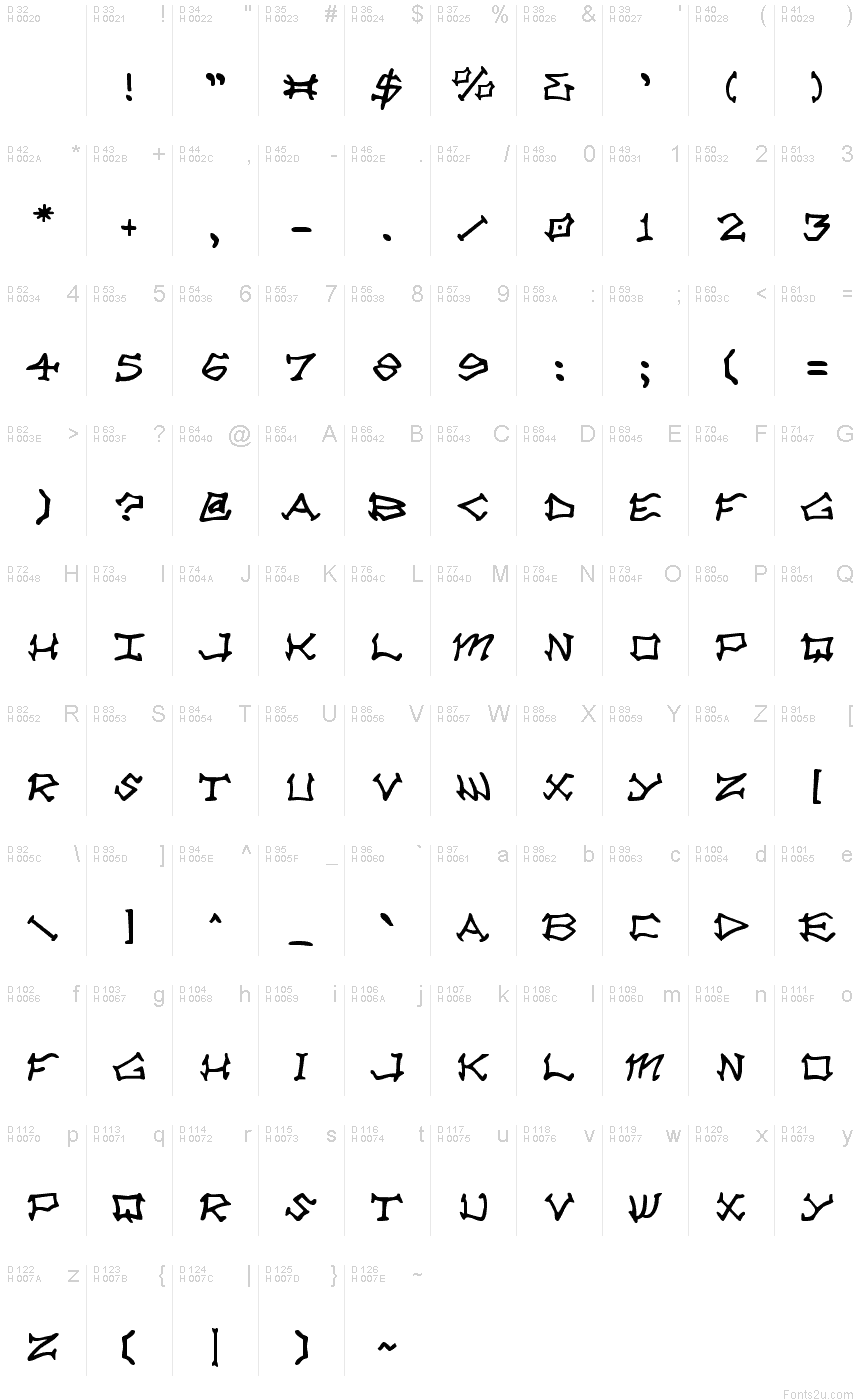
معاينة خط Rad Zad
خط Rad Zad من Iconian Fonts هو خط مجاني مستوحى من كتابات الجرافيتي اليدوية، يتكون من أحرف كبيرة فقط ويتمتع بطاقة الشارع العفوية. تعتمد الحروف على زوايا حادة متعرجة وضربات فرشاة سميكة وأطراف مدببة، مما يمنح المجموعة طابعاً سريعاً ومتمردًا وروحًا كرتونية خفيفة.
ينسجم هذا الخط بشكل طبيعي مع منشورات التزلج وأغلفة المجلات المستقلة وعناوين الألعاب وعناوين الملصقات وتصاميم الهدايا التذكارية، حيث يُفضل أن يبدو الخط المجاني مرسوماً بخط اليد بدلاً من أن يكون مصقولاً. وبما أن الأحرف الكبيرة تجمع بين الوزن الثقيل والزوايا الحادة، فهي مناسبة أيضاً لأسماء الفرق الموسيقية القصيرة وتجارب الشعارات والكلمات التي تتطلب لمسة "تاج" (Tag) جريئة.